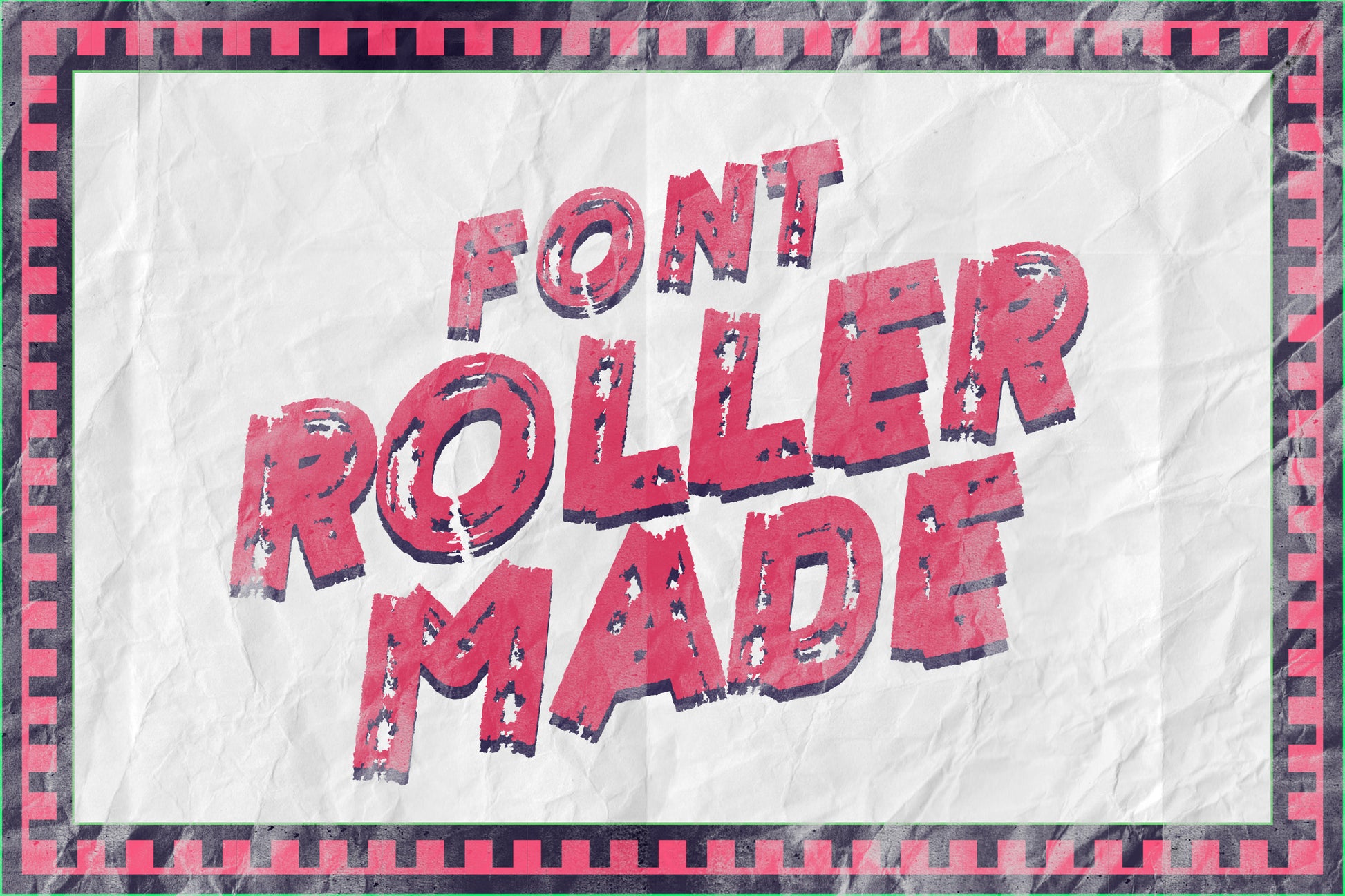
Fuente Roller Made
Esta es una fuente hecha a mano, estilo Roller, adecuada para diseño, diseño de elementos, bodas, eventos, camisetas, logotipos, insignias, calcomanías y un trabajo increíble sobre el verano.